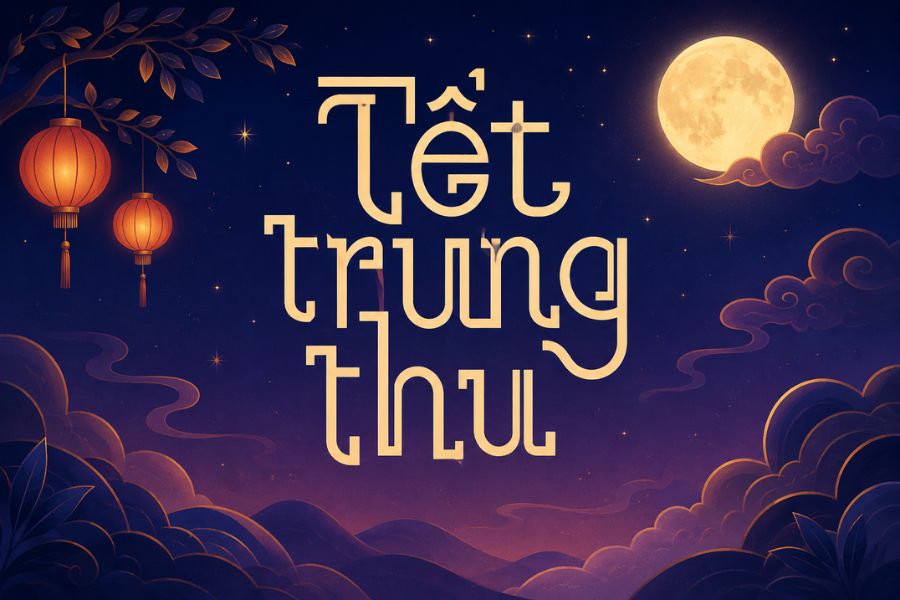
Mùa Tết Trung Thu là thời điểm nhu cầu thiết kế bao bì bánh, banner sự kiện và trang trí không gian tăng cao để khơi gợi không khí sum vầy. Việc sử dụng các bộ font Trung Thu Việt hóa mang phong cách dân gian, uốn lượn mềm mại sẽ giúp các ấn phẩm truyền thông trở nên ấm cúng và đậm đà bản sắc văn hóa.
Đặc trưng thẩm mỹ của bộ font chữ Trung Thu Việt hóa
Điểm đặc trưng của font chữ Trung Thu Việt hóa nằm ở sự kết hợp giữa những đường nét tròn đầy, vững chãi với các nét uốn lượn duyên dáng. Việc xử lý bộ dấu tiếng Việt chuẩn xác giúp các dấu thanh không làm phá vỡ cấu trúc ký tự, đảm bảo nội dung trình bày luôn mạch lạc và giữ đúng tinh thần của bản thiết kế gốc.
Sự tinh tế của các bộ font này còn thể hiện ở khả năng truyền tải năng lượng tích cực và niềm vui. Những đường nét không quá cứng nhắc tạo ra cảm giác gần gũi, phù hợp để thu hút sự chú ý của cả người lớn và trẻ nhỏ. Đây là giải pháp phù hợp cho các thiết kế cần sự mềm mại, mang hơi thở dân tộc nhưng vẫn đáp ứng tiêu chuẩn hiển thị rõ nét trên cả ấn phẩm in ấn lẫn các nền tảng kỹ thuật số.
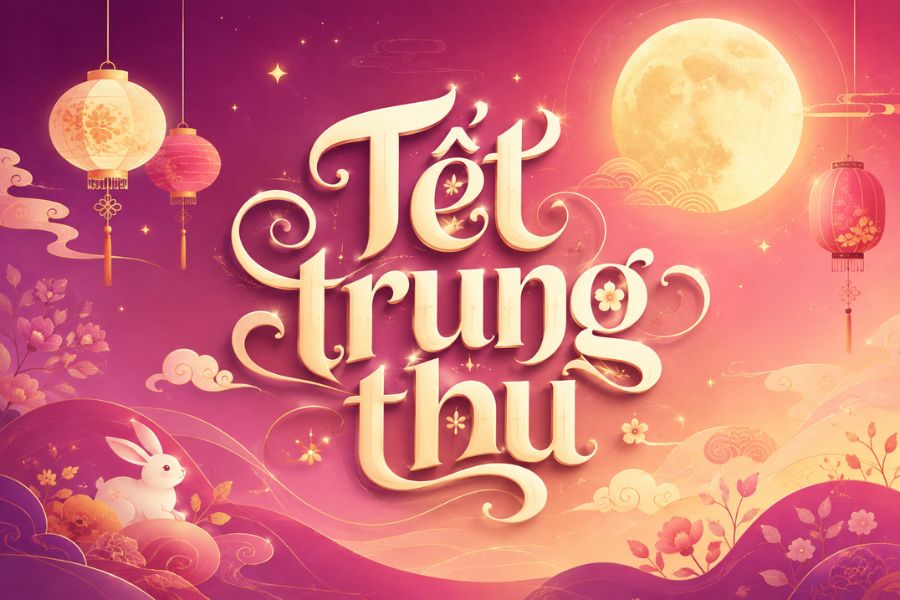
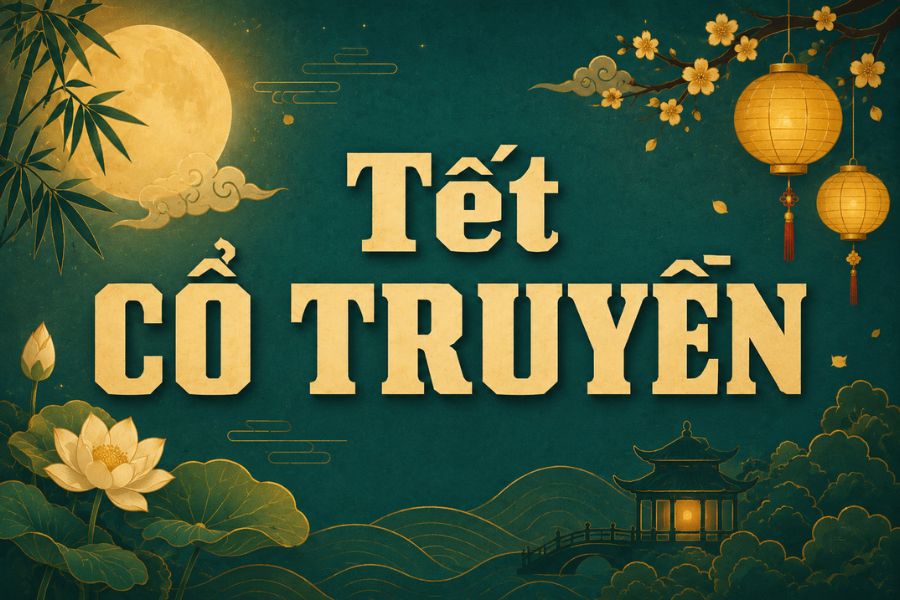
| Phân loại phong cách | Thư pháp cách điệu / Brush / Dân gian |
| Mục đích phù hợp | Bao bì bánh trung thu, Banner, Decor homestay |
Gợi ý phối màu: Để font Trung Thu Việt hóa phát huy hiệu quả thị giác cao, bạn nên phối hợp cùng các tông màu đặc trưng như đỏ rực, vàng đồng, vàng chanh hoặc xanh lá đậm. Việc kết hợp thêm các họa tiết như thỏ ngọc, mây vờn sẽ giúp bản thiết kế trở nên sinh động và giàu cảm xúc hơn.
03 Ứng dụng font Trung Thu vào trang trí và quảng bá
Với vẻ ngoài đậm chất nghệ thuật và sự ấm cúng, bộ font này mang lại giá trị thực tế cao khi được đưa vào các hạng mục trang trí và nhận diện không gian:
- Bảng nhận diện cho sự kiện lễ hội tại Homestay: Những nét chữ uốn lượn của font Trung Thu rất ăn ý khi xuất hiện trên các biển hiệu gỗ hoặc lồng đèn trang trí tại các khu nhà lắp ghép nghỉ dưỡng. Điều này giúp tạo nên một không gian lung linh, thu hút khách lưu trú đến trải nghiệm không khí Tết đoàn viên.
- Thiết kế bao bì quà tặng doanh nghiệp: Sử dụng download font Trung Thu Việt hóa để trình bày tên thương hiệu hoặc lời chúc trên hộp bánh giúp tăng giá trị thẩm mỹ, thể hiện sự chỉn chu và trân trọng đối với đối tác, khách hàng.
- Trang trí khu vực sự kiện và Photobooth: Bạn có thể dùng font này để in decal hoặc cắt chữ nổi trang trí sảnh chờ văn phòng container, khu vui chơi, mang lại không khí rộn ràng và vui tươi cho không gian làm việc.
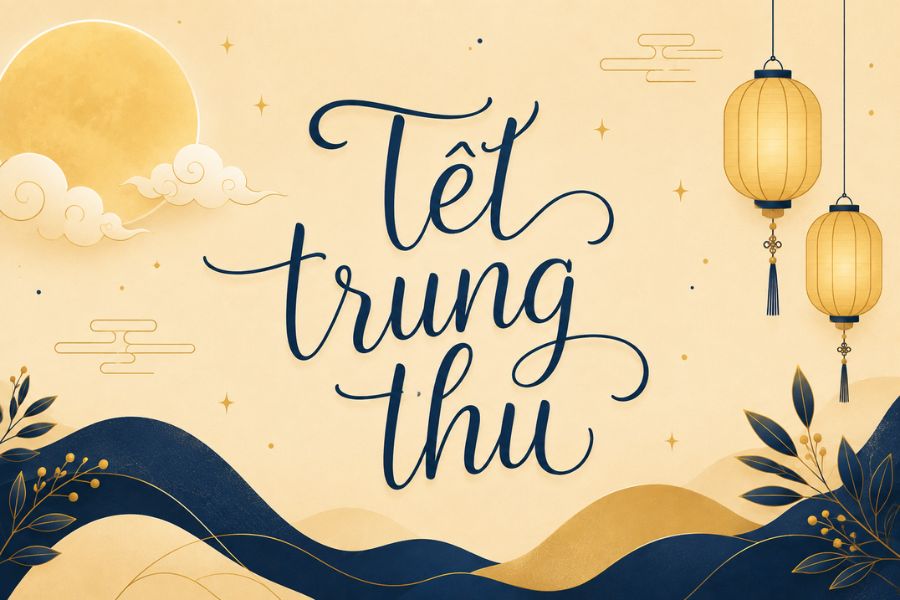
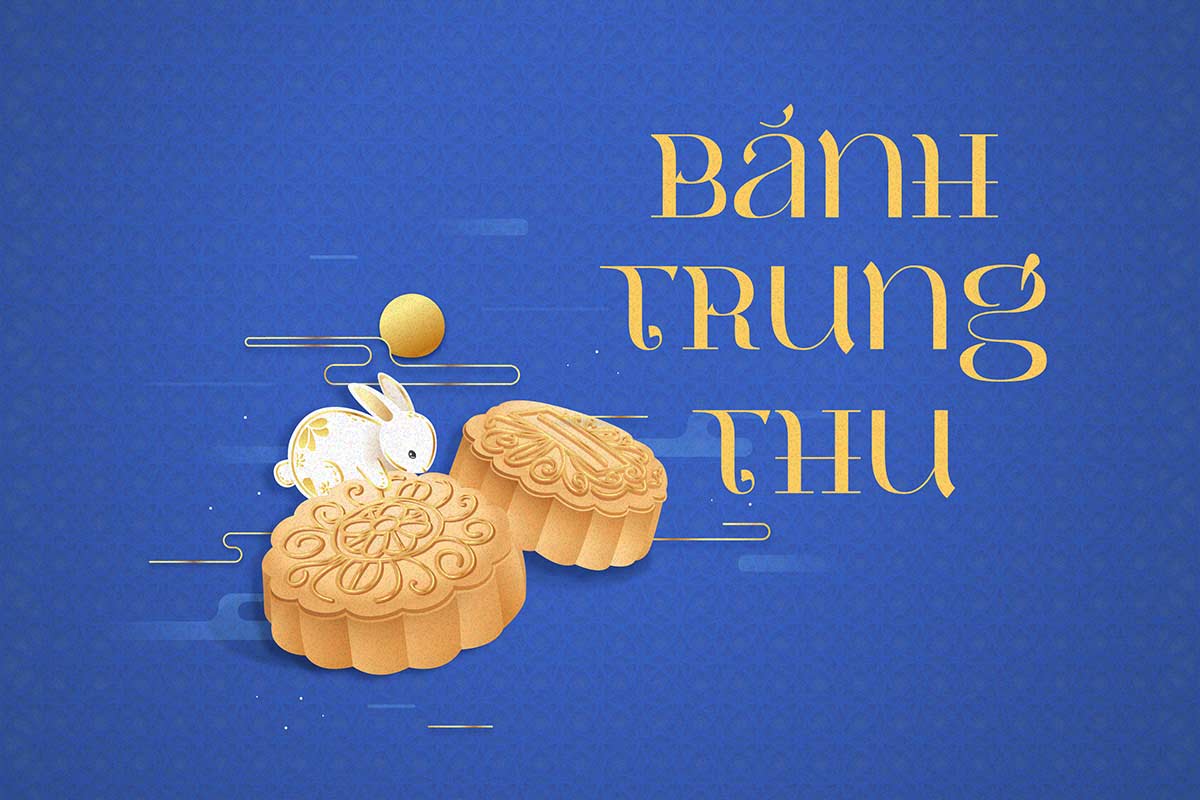
03 Lưu ý khi phối hợp font chữ Trung Thu trong thiết kế
Để khai thác hiệu quả vẻ đẹp của dòng font đặc thù này mà không làm rối mắt người xem, người thiết kế nên lưu tâm một số điểm sau:
- Cân đối mật độ chi tiết: Do font Trung Thu thường có nhiều nét uốn lượn, bạn nên ưu tiên sử dụng cho các tiêu đề chính hoặc slogan ngắn gọn. Tránh dùng cho các đoạn văn bản dài vì sẽ gây mỏi mắt và làm mất đi trọng tâm của bản thiết kế.
- Nới rộng khoảng cách dòng: Hãy đảm bảo khoảng cách giữa các dòng đủ thoáng để các dấu tiếng Việt không bị chồng chéo lên nhau, giúp văn bản giữ được sự minh bạch khi nhìn từ xa.
- Kết hợp cùng font không chân hiện đại: Để tổng thể bản vẽ trông chuyên nghiệp hơn, bạn nên phối font Trung Thu nghệ thuật cùng một font chữ không chân đơn giản cho phần thông tin phụ hoặc các dòng ghi chú kỹ thuật.